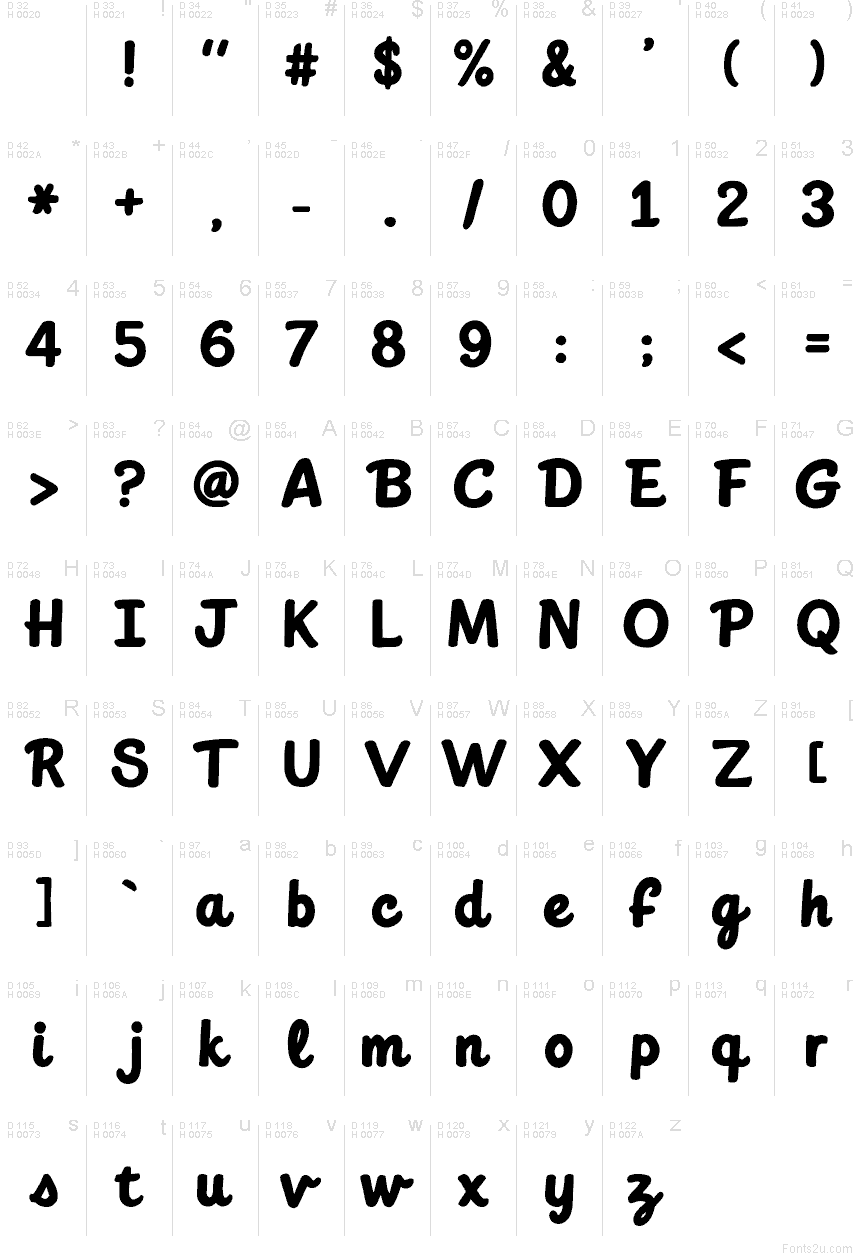
The Secret Mouse di BlackFridayFont è un font brush gratuito con un tratto vivace e dinamico, che dà l'idea di vernice fresca stesa a pennello: fluido, arrotondato e giocoso. Il suo ritmo corposo mantiene la leggibilità delle parole anche nei grandi formati, mentre i bordi morbidi aggiungono una nota amichevole e un tocco artigianale.
The Secret Mouse è perfetto per il branding destinato ai bambini, sticker, etichette per snack o dolci, poster creativi, miniature di YouTube, citazioni sui social, inviti a feste e merchandising informale. Abbina questo font gratuito a una sans-serif geometrica pulita per i dettagli più piccoli e lascia che The Secret Mouse domini i titoli, dove il suo carattere distintivo può esprimersi al meglio.